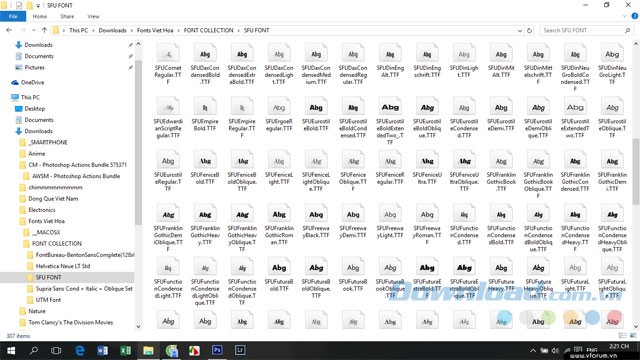
Bộ Font chữ Việt hóa bao gồm 500 Font chữ đẹp được tối ưu cho Photoshop . Bộ sưu tập này hỗ trợ đắc lực cho các nhà thiết kế trong việc lựa chọn font chữ phù hợp với từng dự án.
Tuy nhiên, các nhà thiết kế và Designer chuyên nghiệp đòi hỏi sự đa dạng và độc đáo trong lựa chọn font chữ. Họ cần những kiểu chữ có đường nét uốn lượn, hình dáng độc đáo để tạo nên sự khác biệt cho tác phẩm của mình.
Bộ sưu tập này mang đến 500 font chữ đã được Việt hóa, tương thích hoàn hảo với phần mềm Photoshop.
Các loại font được Việt hóa sở hữu vẻ đẹp tinh tế, đáp ứng đa dạng nhu cầu thiết kế.
Người dùng có thể tùy biến kiểu dáng, màu sắc và kích thước font chữ để tạo nên những tác phẩm độc đáo.
Bộ font chữ Việt hóa này sẽ hỗ trợ bạn lựa chọn nhanh chóng kiểu chữ ưng ý, góp phần nâng cao hiệu quả học tập và công việc.